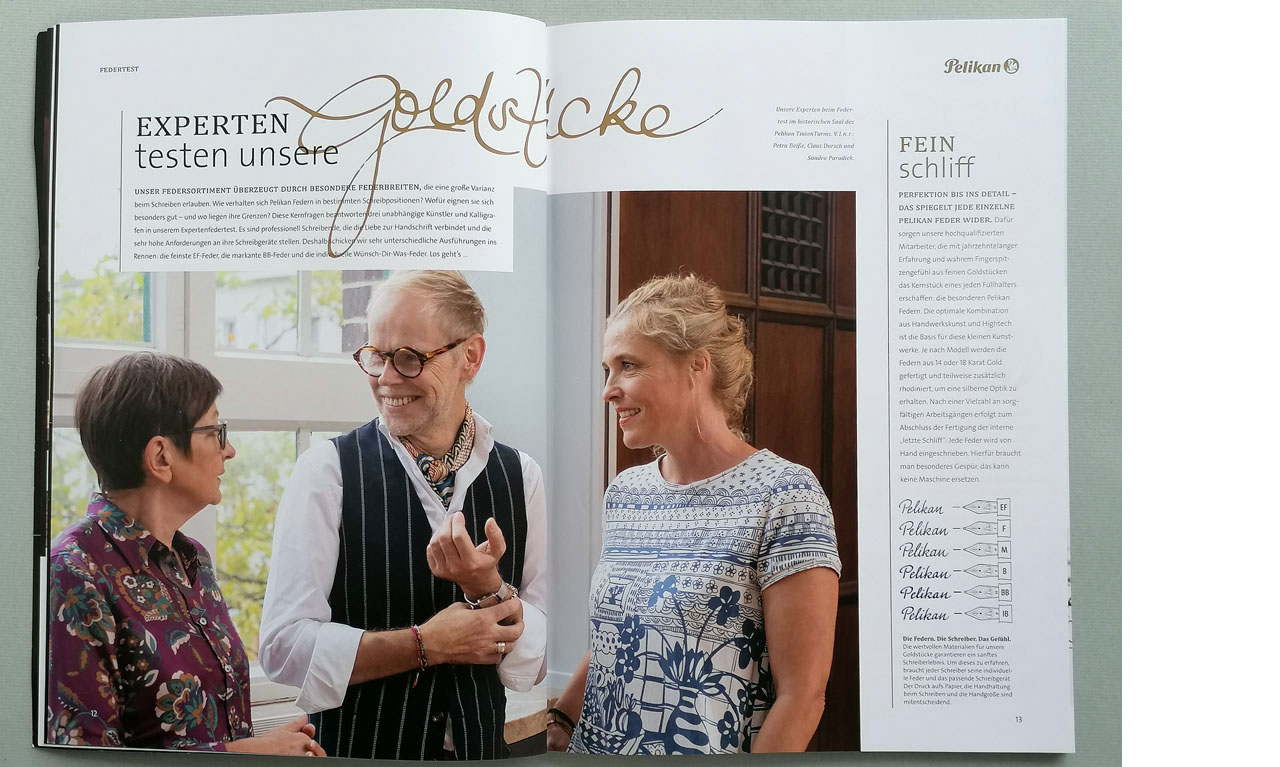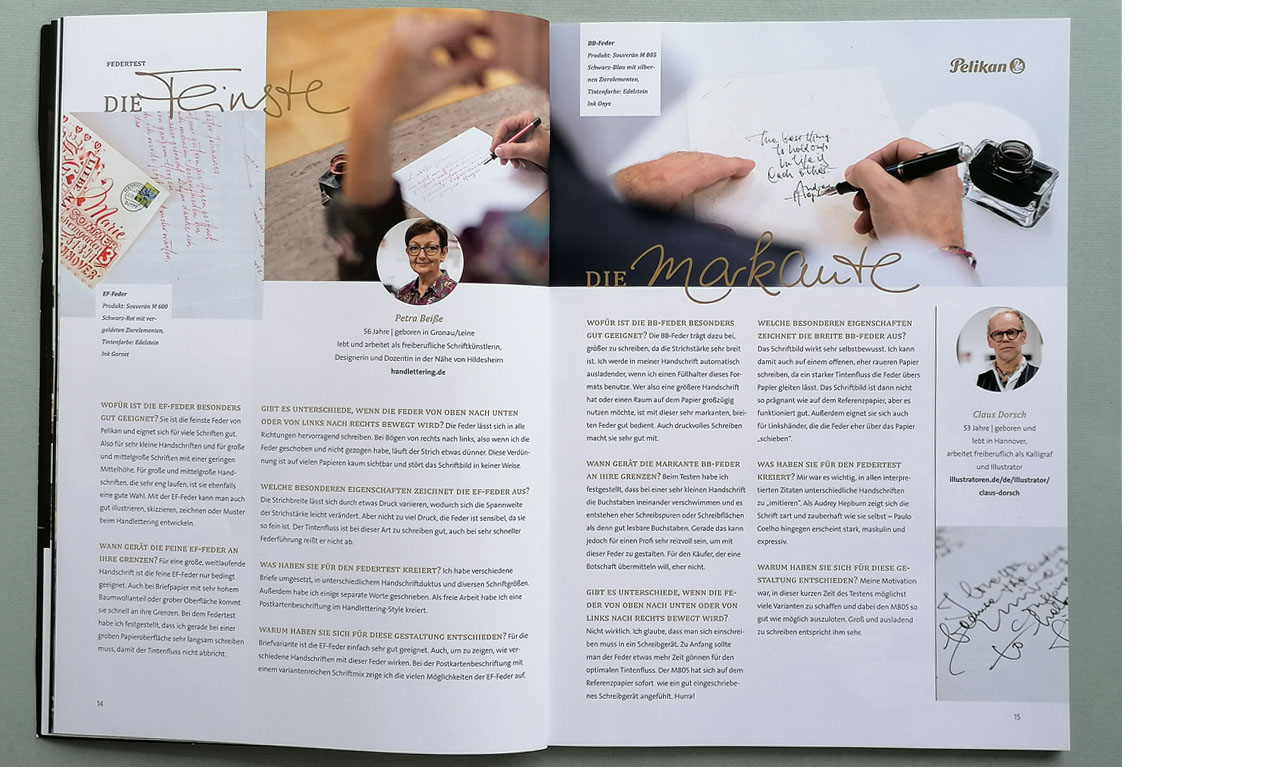
Drei Schriftexperten testen drei Federstärken
Abbildung unten:
Handlettering Postkarte
mit einer EF-Feder umgesetzt
Was das Besondere an jeder Feder ist, wann welche Feder an ihre Grenzen kommt, für welche Handschriftcharaktere welche Feder geeignet ist u. v. m. erfährt der Interessierte im neuen Pelikan-Katalog für hochwertige Schreibgeräte.
Ich freue mich, dass ich dabei war und die extra feine EF-Feder des Souverän M 600 ausgiebig testen durfte.
In der ersten Testphase habe ich die Feder für die unterschiedlichsten Handschriftcharaktere getestet. Die EF-Feder eignet sich nicht nur für kleine Handschriften sehr gut, sondern auch für mittelgroße bis große Handschriften, die sehr eng laufen sowie für Handschriften mit sehr niedrigen Mittelhöhen.
Auch was den Druck beim Schreiben auf die Feder betrifft, deckt die EF-Feder ein breites Spektrum ab. Beim Schreiben mit wenig Druck sowie auch mit erhöhtem Druck gleitet die Feinste von Pelikan problemlos übers Papier und der Tintenfluss reist nicht ab. Lediglich die Strichstärke verändert sich etwas.
Da ich beruflich nicht nur auf Handschriften sondern auch auf Lettering (das Zeichnen von Schriften) spezialisiert bin, habe ich in der zweiten Testphase als freie Arbeit eine Postkarte im Lettering-Style kreiert (Abbildung oben). Auch für diese Disziplin ist die Feder und der Souverän M600 hervorragend geeignet. Das Schreibgerät ist sehr gut ausbalanciert und sorgt somit für ermüdungsfreies Zeichnen. Die Feder gleitet in alle Richtungen problemlos über das Papier und beim neuen Ansetzen der Feder ist der Tintenfluss ohne Verzögerung vorhanden.
Anmerkung:
Die handschriftlichen Worte »Goldstücke«, »Feinste« und »Markante« stammen nicht aus meiner Feder.